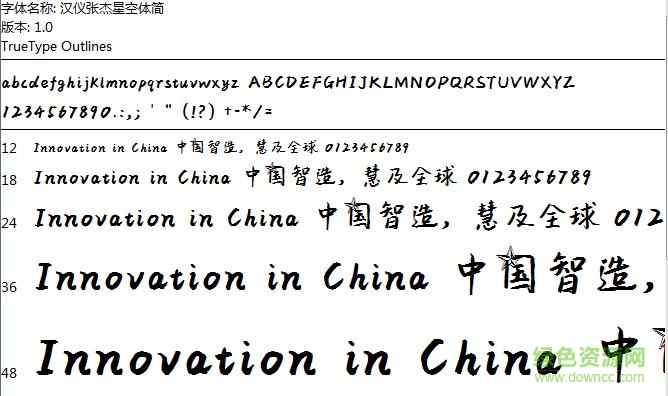
漢儀張杰星空體ttf是一款專(zhuān)為喜歡張杰的朋友準(zhǔn)備的字體,這款字體最大的特色就是很多字符上都有一個(gè)大星星,非常有意思,喜歡趕緊下載!
漢儀張杰星空體是漢儀字庫(kù)明星字體中的一款,這款字體在漢儀張杰體的基礎(chǔ)上修改而來(lái),在某些字體上適當(dāng)?shù)募尤肓诵切?,提升的整體的神秘感和可辨識(shí)性!